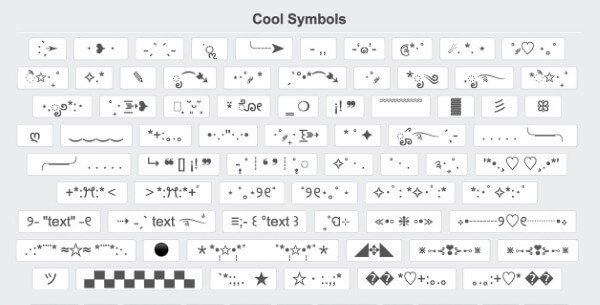
Cách tạo tên FB đẹp với ký tự đặc biệt & font chữ ấn tượng
Trong thời đại mạng xã hội phát triển mạnh mẽ, một cái tên Facebook không chỉ để nhận diện mà còn thể hiện cá tính riêng. Vì vậy, việc tạo tên FB đẹp bằng ký tự đặc biệt, font chữ độc đáo hay biểu tượng sáng tạo đang trở thành xu hướng được nhiều người quan tâm. Bài viết dưới đây sẽ giúp bạn hiểu rõ cách tạo tên FB đẹp, cách dùng công cụ hỗ trợ và những lưu ý quan trọng để sở hữu một tên hiển thị ấn tượng nhưng vẫn an toàn khi sử dụng.
Tổng hợp cách tạo tên FB đẹp
Việc tạo tên FB đẹp ngày nay không còn đơn giản chỉ là ghép tên và họ, mà đã trở thành một “nghệ thuật cá nhân hóa”. Người dùng có thể biến tên thật thành một phiên bản độc đáo hơn bằng cách sử dụng ký tự đặc biệt, font chữ nghệ thuật hoặc các biểu tượng trang trí.
Một số cách tạo tên Facebook đẹp phổ biến và dễ thực hiện
Một số cách phổ biến để tạo tên FB đẹp gồm:
• Sử dụng ký tự đặc biệt như ★, ✿, ✧, ♡ để tạo điểm nhấn
• Chuyển đổi chữ thường sang font chữ nghệ thuật như chữ nghiêng, chữ đậm hoặc chữ cách điệu
• Kết hợp kaomoji (biểu cảm bằng ký tự như (✿◠‿◠), (•̀ᴗ•́)و ̑̑)
• Thêm dấu cách đặc biệt hoặc ký hiệu trang trí ở đầu/cuối tên
Những cách này giúp tạo tên FB đẹp trở nên thu hút hơn, đồng thời thể hiện rõ phong cách cá nhân của người dùng.
Hướng dẫn dùng công cụ tạo tên FB đẹp
Hiện nay, để tạo tên FB đẹp, bạn không cần phải tự thiết kế thủ công mà có thể sử dụng các công cụ hỗ trợ trực tuyến. Các website tạo font chữ và ký tự đặc biệt giúp bạn chuyển đổi tên chỉ trong vài giây.
Sử dụng các công cụ giúp tạo tên Facebook đẹp
Một số công cụ phổ biến:
• Lingojam Fancy Text Generator
• CoolSymbol
• Fonts For Instagram / Facebook tools
• Symbol and Kaomoji generators
Cách sử dụng khá đơn giản: Bạn chỉ cần nhập tên của mình vào ô công cụ, sau đó hệ thống sẽ tự động hiển thị nhiều kiểu chữ khác nhau. Bạn có thể chọn mẫu phù hợp nhất để tạo tên FB đẹp rồi sao chép và dán trực tiếp vào Facebook.
Ngoài ra, một số công cụ còn cho phép chèn biểu tượng, emoji hoặc kaomoji giúp tên trở nên sinh động hơn. Tuy nhiên, khi sử dụng cần cân nhắc để đảm bảo tên vẫn dễ đọc và không quá rối mắt.
Nguyên tắc đặt tên Facebook đẹp cá tính, dễ nhớ, không quá dài, không lạm dụng ký tự
Khi tạo tên FB đẹp, nhiều người thường mắc sai lầm là lạm dụng quá nhiều ký tự đặc biệt hoặc font chữ phức tạp, khiến tên trở nên khó đọc hoặc khó tìm kiếm.
Một số nguyên tắc quan trọng cần lưu ý:
• Tên Facebook nên ngắn gọn và dễ nhớ. Một cái tên quá dài sẽ khiến người khác khó ghi nhớ và khó tìm kiếm khi cần kết bạn.
• Việc sử dụng ký tự đặc biệt cần có chừng mực. Nếu quá nhiều biểu tượng trang trí, tên sẽ mất đi tính tự nhiên và có thể gây khó chịu cho người xem.
• Một tên Facebook đẹp nên phản ánh cá tính hoặc phong cách của người dùng. Ví dụ, người thích sự nhẹ nhàng có thể chọn phong cách tối giản, trong khi người cá tính mạnh có thể chọn phong cách ngầu hoặc nổi bật.
• Cuối cùng, cần đảm bảo tên vẫn có thể đọc được dễ dàng sau khi tạo tên FB đẹp, tránh biến tên thành một chuỗi ký tự khó hiểu.
Một số nguyên tắc đặt tên Facebook đẹp và cá tính
Tổng hợp mẫu tên FB đẹp theo phong cách
Để giúp bạn dễ hình dung hơn khi tạo tên FB đẹp, dưới đây là một số phong cách phổ biến được nhiều người yêu thích.
Phong cách dễ thương thường sử dụng ký tự mềm mại và biểu tượng đáng yêu:
• Bunny Linh
• Meo Meo
• Sweetie An
Phong cách ngầu thường kết hợp font đậm và ký tự mạnh mẽ:
• Khoa Ring
• Dark Soul
• Hùng Legend
Phong cách sang chảnh thường tối giản nhưng tinh tế:
• Anna
• Lily
• Minh Elite
Phong cách tối giản lại tập trung vào sự gọn gàng:
• Nam
• Huy
• Linh
Những gợi ý này giúp bạn dễ dàng lựa chọn khi muốn tạo tên FB đẹp phù hợp với hình ảnh cá nhân trên mạng xã hội.
Những mẫu tên Facebook đẹp theo phong cách cá nhân
Lưu ý ký tự đặc biệt quá nhiều có thể bị FB từ chối hoặc khó tìm kiếm
Mặc dù việc tạo tên FB đẹp bằng ký tự đặc biệt mang lại sự độc đáo, nhưng nếu sử dụng không hợp lý có thể gây ra một số vấn đề. Facebook có hệ thống kiểm duyệt tên hiển thị, vì vậy những tên quá phức tạp hoặc chứa quá nhiều ký tự đặc biệt có thể bị từ chối thay đổi.
Không nên đặt quá nhiều ký tự đặc biệt có thể khiến tên từ chối hoặc khó tìm kiếm
Ngoài ra, khi tên quá khó đọc, người khác sẽ gặp khó khăn trong việc tìm kiếm tài khoản của bạn. Điều này ảnh hưởng đến khả năng kết nối và xây dựng mạng lưới bạn bè. Vì vậy, khi tạo tên FB đẹp, bạn nên ưu tiên sự cân bằng giữa thẩm mỹ và tính thực tế, đảm bảo tên vừa đẹp vừa dễ sử dụng.